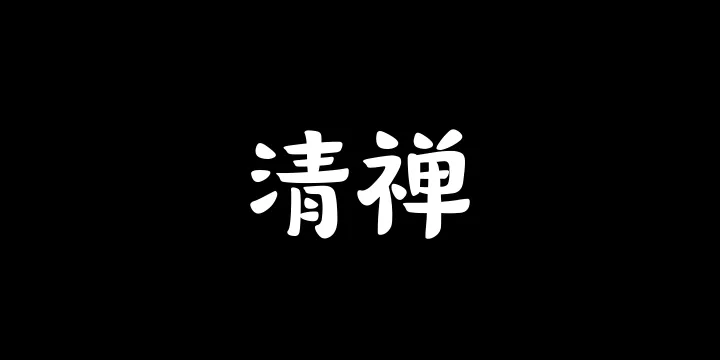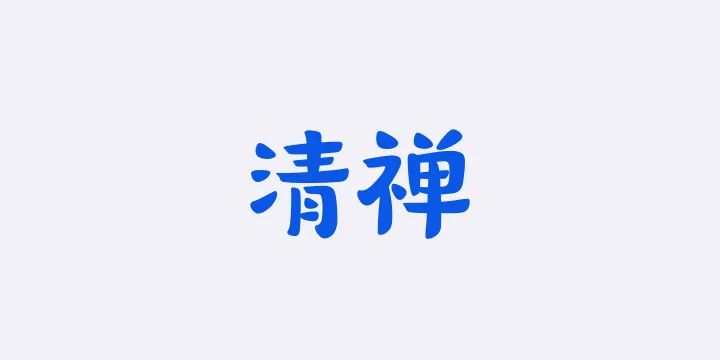
山海清禅W By 山海字库 商用字体
字体全名: 山海清禅W
字体简介: 山海清禅,是一款全新的字体,包含汉字9169个,符号200+个,是一款禅意风字体。该字体字形优美文雅,禅韵内敛,书法的运笔走势蕴含其中,流畅自然,蕴含东方审美韵味,尽显优雅从容,秀雅清新,禅韵十足,整体给人一种放松禅韵的视觉效果和自由洒脱之感。
所属分类: 手写体